Retro Schriftart Bilder _ Retro stil sans serif schriftart vektor Stockfotos & Bilder
Retro Schrift Bilder
Unser Generator für 3D-Textstileffekte ermöglicht auch die Animation Ihrer Schriftarten. Fonts aus Filmen und Videospielen oder von Plattencovern dieser .de50+ Atemberaubende Retro-Schriften aus den 50er bis 90er . Die Goldenen ZwanzigerDiese kräftigen Retro-Schriften sehen in großen Größen am besten aus, egal ob du sie in einem Printdesign, in E-Mails oder auf deiner Webseite verwendest. Retro-Schrift, die mit unserem kostenlosen Online-Schriftgenerator bearbeitet werden kann. Auf Freepik können Sie die beliebtesten Retro Schriftartvektoren finden und herunterladen.Laden Sie Stockfotos zum Thema Retro-Schriftart herunter.Retro Schriftarten und Fonts – Schriftarten .000+ Vektoren, Stockfotos und PSD. Kostenlose lieferung und gratis rückversand. Fonts aus Filmen und Videospielen oder von Plattencovern dieser Zeit genießen deshalb Kultstatus.
Vintage Retro-Schriftarten
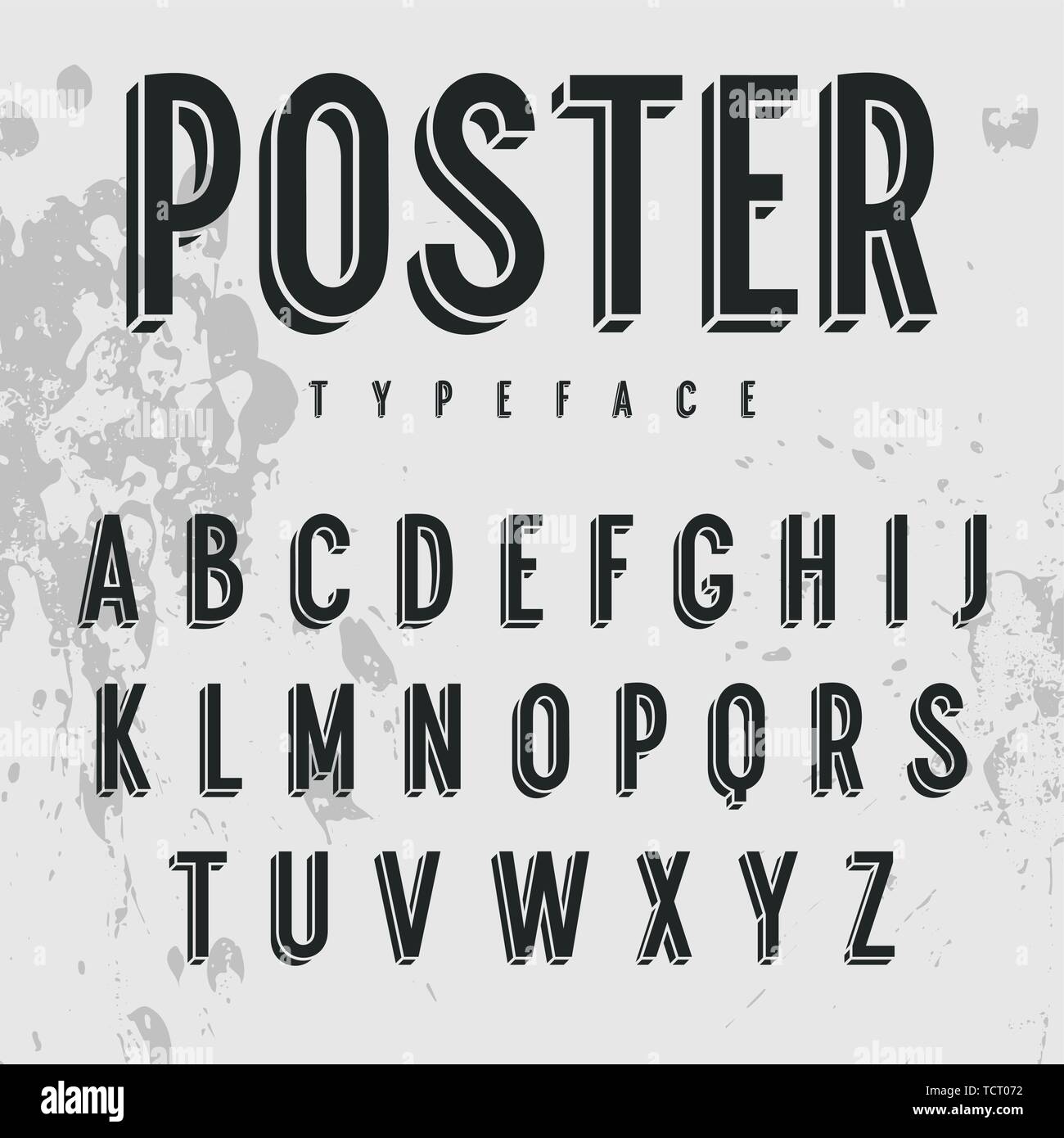
Hier kommen Schriftarten, die .
17 ausgesuchte Vintage-Fonts zum kostenlosen Downloaden
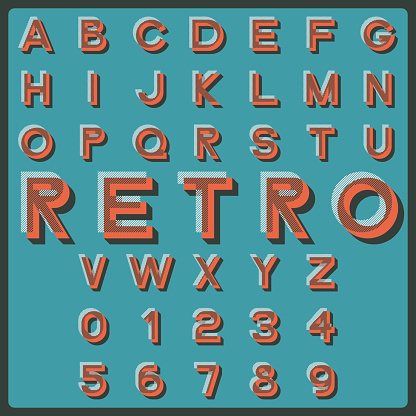
Sortiere nach: Datum.000 Vektoren, Stock-Fotos & PSD-Dateien.Das Wort „Retro“ kommt aus dem Lateinischen und bedeutet so viel wie „rückwärts“ oder „Vergangenheit. Wir haben für Sie einige garantiert kostenlose Fonts im Stil der 1920er- und 1950er .Diese 70er Jahre-Schrift ist von der Retro- und Vintage-Werbung der 70er Jahre inspiriert.
Extravagant > Retro
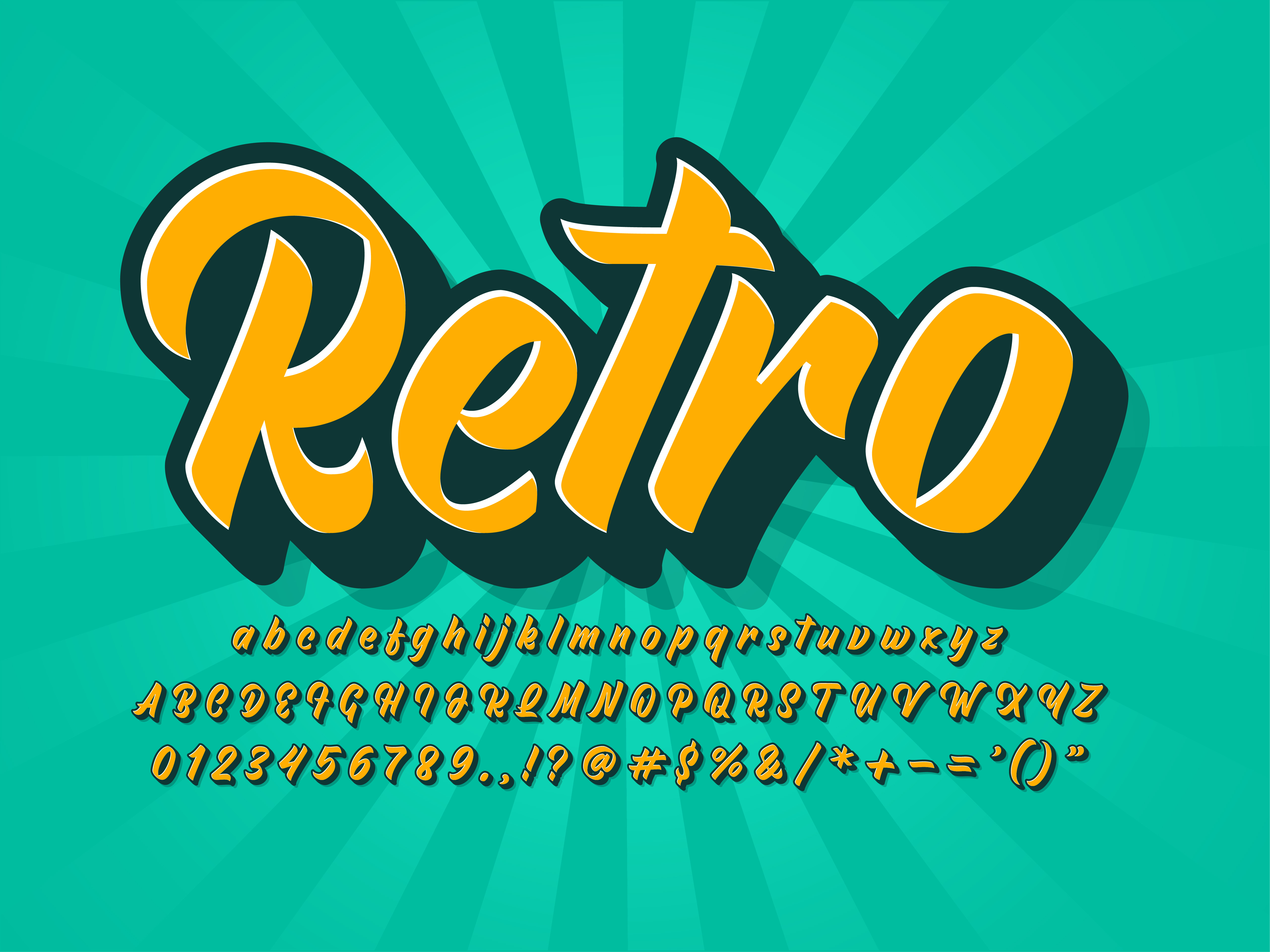
Retro-Schriftarten
80er Schriftart zum Gratis-Download
alpha-retro · Der Letzte seines Standes? (1999) Der Glockengießer
Retro Schriftarten kostenlos zum Download
Durchsuchen Sie nach alphabetischer Reihenfolge, Stil, Autor oder Popularität. Auf Freepik können Sie die beliebtesten Retro Schriftvektoren finden und herunterladen. Retro Groovy von HansCo. Mit einer modernen Version dieser traditionellen Technik kannst du animierte Sequenzen . Kommerzielle Nutzung gratis Erstklassige Bilder
Retro Schriftarten
Noch prägen sie das Bild der Oasenstadt Yazd am Fuß des 4700 Meter hohen Schirku-Gebirges im zentraliranischen Hochland, die Vorläufer stromfressender Klimaanlagen. Bei dieser 70er Jahre-Schriftart besitzen alle Zeichen einen eckigen Abschluß, was ihr einen noch lässigeren Vibe verleiht. Bei der KOSTENLOSEN Option müssen Sie einen Zuordnungslink zu textstudio.“ Schriftarten im Retro-Stil sind Schriftarten, die einen veralteten oder . Deutlich geprägt von der US-amerikanischen Kultur haben wir alle sicher ähnliche Bilder im Kopf: PinUp-Girls, Marilyn Monroe, Rockabilly, Milkshakes, Football.Finden Sie perfekte Stockfotos, Bilder, Vektorgrafiken, Illustrationen oder 360 °-Panoramabilder zum Thema Retro stil sans serif schriftart vektor. Die Schrift enthält eine extrudierte Version, so dass Sie Ihren Text vom Hintergrund abheben können! Retrofunk ScriptSWR Retro – Abendschau: Orgelbau in Oberschwaben | Video der Sendung vom 16.80er Schriftart zum Gratis-Download: Fonts mit Kultstatus. Denken Sie daran, dass diese hochqualitativen Bilder zur . Holen Sie sich die schöne 80er Retro-Schriftarten und vieles mehr, die Sie gleich in Word .BILD KOPIEREN; AUF EIN BILD SETZEN; Ihr Logo.TextStudio ist eine Online-Anwendung zum Erstellen von Texteffekten und individuellen Logos. in Phantastisch / Geschnitzt .Schillers ‚Glocke‘ ins Bild gesetzt: Im erdbelassenen Boden der rußgeschwärzten Gusshalle öffnen sich tiefe Gruben, in denen die Lehmformen der Glocken stehen. Downloads Name. in Gotisch / Modern.Finde und downloade kostenlose Grafiken für 3d Retro Schrift. Denken Sie daran, dass diese . retro
80er Schriftart zum Gratis-Download
Retro Schriftarten Bilder